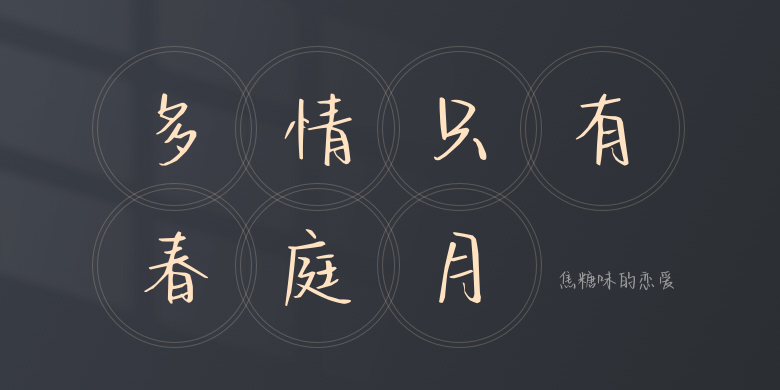
焦糖味的恋爱
焦糖味的恋爱,这款字体结构工整、笔画清晰,兼顾美观与易读性,适用于标题、正文、海报、包装、LOGO 等多种场景。字形优雅稳定,风格百搭耐看,适配日常排版与创意设计,让文字呈现更舒适、更具质感。焦糖味的恋爱一笔一画,皆是细节,以均衡的比例、流畅的线条打造舒适视觉体验,字形端正大气,风格简约现代。无论是商业设计、品牌宣传还是日常排版,都能轻松驾驭,让文字更有格调与力量。焦糖味的恋爱字体下载。